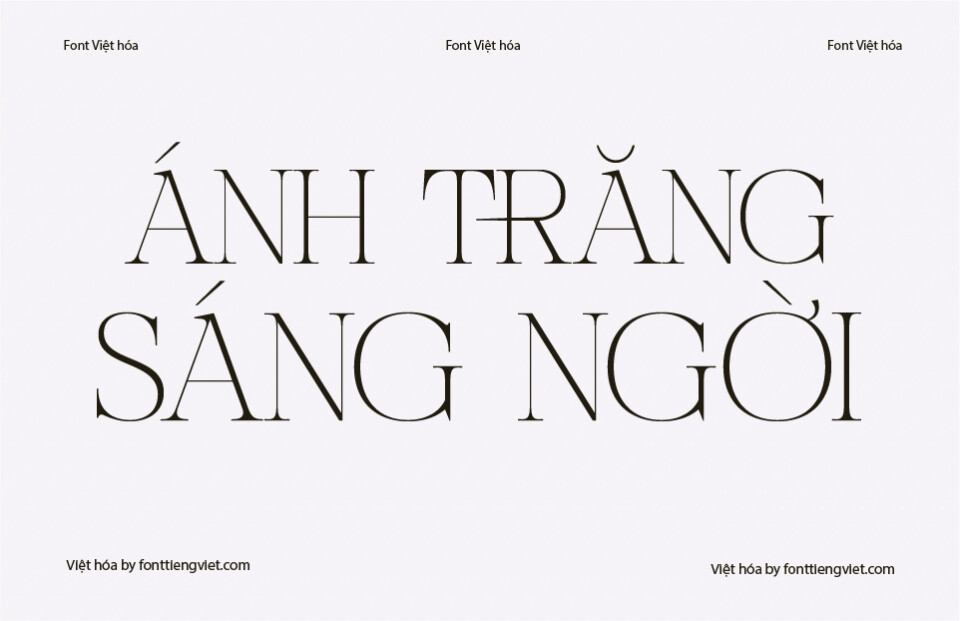
Font Việt hóa 1FTV VIP Nocashe
Font Việt hóa 1FTV VIP Nocashe: Bộ Font Hiện Đại Dành Cho Thiết Kế Sáng Tạo
Trong thế giới thiết kế đồ họa hiện nay, việc lựa chọn một bộ Font Miễn Phí chất lượng luôn là ưu tiên hàng đầu của các nhà sáng tạo. Đặc biệt, bộ Font Việt hóa 1FTV VIP Nocashe đang trở thành tâm điểm chú ý nhờ phong cách hiện đại và khả năng ứng dụng linh hoạt. Đây là một phông chữ được tinh chỉnh kỹ lưỡng để phù hợp với bảng mã tiếng Việt, giúp người dùng loại bỏ hoàn toàn nỗi lo về lỗi hiển thị dấu câu. Với các bạn học sinh, sinh viên hay những người mới bắt đầu làm quen với thiết kế, việc sở hữu bộ font này sẽ giúp các bài thuyết trình, ấn phẩm truyền thông hay thiệp mời trở nên chuyên nghiệp và thu hút hơn bao giờ hết.
Khám phá sức hút của Font Việt hóa 1FTV VIP Nocashe
Bộ Font Việt hóa 1FTV VIP Nocashe không chỉ đơn thuần là một công cụ gõ văn bản mà còn là nguồn cảm hứng nghệ thuật độc đáo. Đặc điểm nổi bật của nó nằm ở những đường nét thanh thoát, gọn gàng nhưng vẫn giữ được sự mạnh mẽ cần thiết. Khi sử dụng trong các tiêu đề lớn hoặc biểu ngữ, font chữ này tạo ra một diện mạo sang trọng và tinh tế, giúp thông điệp truyền tải đến người xem một cách trực diện nhất. Đây là lựa chọn hoàn hảo cho các dự án thiết kế thương hiệu, bìa sách hoặc các sản phẩm in ấn đòi hỏi tính thẩm mỹ cao và sự chỉn chu trong từng chi tiết nhỏ.
Ưu điểm nổi bật khi sử dụng Nocashe Việt hóa
Điều khiến Font Việt hóa 1FTV VIP Nocashe vượt trội hơn so với các bộ font thông thường chính là sự đa dạng trong các biến thể độ dày (weight). Người dùng có thể dễ dàng chuyển đổi từ nét mảnh tinh tế sang nét đậm đầy quyền lực để tạo điểm nhấn cho nội dung. Hơn nữa, tính tương thích cao của nó với các phần mềm thiết kế phổ biến như Adobe Photoshop, Illustrator hay Canva giúp quy trình làm việc trở nên mượt mà. Khả năng hiển thị sắc nét trên cả màn hình kỹ thuật số và các bản in giấy cũng là một điểm cộng lớn giúp bộ font này giữ vững vị thế trong lòng cộng đồng designer Việt Nam.
Ứng dụng thực tế trong học tập và công việc
Trong môi trường giáo dục, việc sử dụng Font Việt hóa 1FTV VIP Nocashe giúp các bài giảng điện tử của giáo viên trở nên sinh động và dễ theo dõi hơn. Học sinh có thể dùng font này để làm báo cáo nhóm hoặc thiết kế poster cho các hoạt động ngoại khóa. Đối với các doanh nghiệp, đây là giải pháp tiết kiệm chi phí nhưng vẫn đảm bảo tính chuyên nghiệp cho các chiến dịch marketing. Nhờ việc được Việt hóa chuẩn xác, bạn có thể tự tin soạn thảo những nội dung tiếng Việt phức tạp mà không sợ bị nhảy lỗi phông hay sai lệch khoảng cách giữa các ký tự, tạo nên sự đồng nhất hoàn hảo.
Kết luận về bộ font chữ VIP đẳng cấp
Tóm lại, Font Việt hóa 1FTV VIP Nocashe là một tài nguyên quý giá mà bất kỳ ai yêu thích thiết kế cũng nên sở hữu trong bộ sưu tập của mình. Với sự kết hợp hoàn hảo giữa thẩm mỹ và tính ứng dụng, nó giúp nâng tầm mọi sản phẩm nội dung từ đơn giản đến phức tạp. Đừng bỏ lỡ cơ hội làm mới các dự án của bạn với bộ Font Miễn Phí, Font Việt Hóa, Font Việt hóa 1FTV VIP Nocashe ngay hôm nay để trải nghiệm sự khác biệt. Chắc chắn rằng, sự xuất hiện của phông chữ này sẽ mang lại luồng gió mới, giúp công việc sáng tạo của bạn trở nên thú vị, chuyên nghiệp và đạt được hiệu quả truyền thông cao nhất trong mắt người xem.